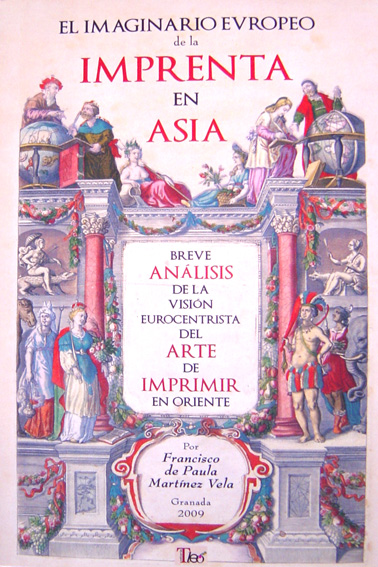
Acaba de llegar a nuestra manos un pequeño libro que, con una cautivadora portada histórica alusiva, nos ha llamado enormemente la atención.
Lleva por título El imaginario europeo de la imprenta en Asia y su autor el historiador de la tipografía Francisco de Paula Martínez Vela.
En el mismo su autor analiza, partiendo de textos históricos, la visión que sobre la imprenta y su invención hemos creado en Europa a lo largo del tiempo salvaguardando nuestros intereses y ajustando los hechos a nuestra conveniencia.
Se trata, sin lugar a dudas, de un texto que no dejará de sorprendernos ya que auna diversas y reputadas «voces», de gran peso en la historia de la tipografía, y las pone al servicio del desarrollo de la idea de que cada país escribe la historia desde su punto de vista, tanto los grandes sucesos políticos como culturales.
Destacar asimismo que la belleza de la obra no se limita a su portada, sino que su interior también está compuesto con un estilo clásico, al que contribuyen sobremanera los finos ornamentos recuperados de las obras impresas por Pierre Simon Fournier que dotan a la página de una belleza y pulcritud que quizás hemos olvidado en la imprenta moderna.